泰語(yǔ)標(biāo)準(zhǔn)字體是一款包括了常用的十五款泰國(guó)語(yǔ)字體的字體打包合集,方便用戶更好的運(yùn)用泰國(guó)文字,不僅便于泰國(guó)朋友的書寫,也適合設(shè)計(jì)師們的引用,綠色資源網(wǎng)獨(dú)家推薦!
Angsana New
AngsanaUPC
bromalliaUPC
Cordia New
CordiaUPC
DilleniaUPC
EucrosiaUPC
FreesiaUPC
IrisUPC
JasmineUPC
JS wansika
KodchiangUPC
Leelawadee
LilyUPC
thai
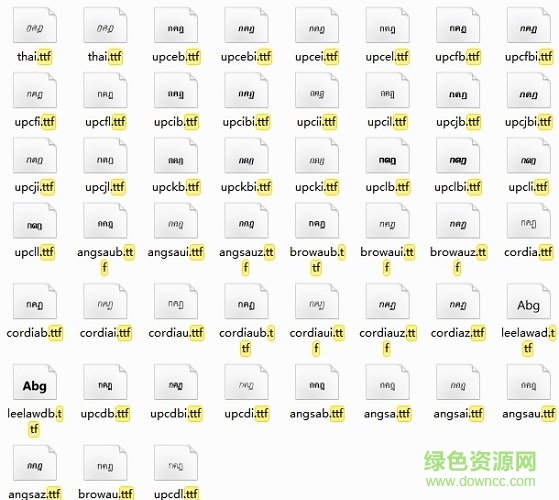
泰文是用來(lái)標(biāo)寫泰語(yǔ)的文字,在泰國(guó)使用。泰文屬于元音附標(biāo)文字,即用在輔音字母的四周標(biāo)示代表元音的符號(hào)。泰文由著名的素可泰王朝創(chuàng)建者,Si Intharathit國(guó)王的第二個(gè)兒子,也就是第三任國(guó)王坎亨(Ramkhamhaeng)于1283年發(fā)明,被稱為“素可泰文”,字母系統(tǒng)來(lái)源于古印度梵文。泰語(yǔ)是泰國(guó)的官方語(yǔ)言。泰語(yǔ)是一種分析型語(yǔ)言,不同的聲調(diào)有區(qū)分詞匯和語(yǔ)法的作用。